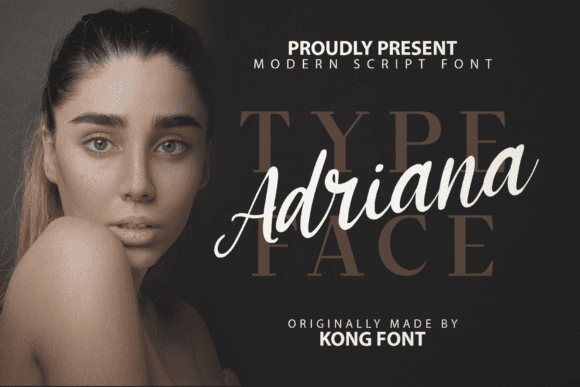
Fonte Adriana para títulos, pôsteres e projetos de identidade visual.
Esta é uma fonte de exibição moderna, criada para designers que precisam de clareza e elegância em tipografia de grande formato. Adriana apresenta traços refinados e espaçamento equilibrado, tornando-a ideal para títulos, layouts editoriais e identidade visual de marcas.
Como fonte, Adriana traz precisão e estilo a logotipos, materiais de marketing e composições de pôsteres. Seu design minimalista garante legibilidade, mantendo uma forte identidade visual em todas as mídias.
Seja para construir uma marca, criar peças gráficas promocionais ou desenvolver composições tipográficas arrojadas, Adriana oferece a flexibilidade e o requinte que seu trabalho exige.
O que você pode fazer
- Manchetes de revistas e da web
- Títulos de pôsteres e folhetos
- Logotipos e marcas denominativas
- Embalagem e sinalização do produto
- Banners ousados e campanhas visuais
Por que você vai adorar
- Design moderno, limpo e profissional.
- Excelente legibilidade em tamanhos grandes e pequenos.
- Ideal para branding e textos de alto impacto.
P: Que tipo de fonte é Adriana?
A: Adriana é uma fonte de exibição elegante, projetada para títulos impactantes, identidade visual moderna e pôsteres estilosos.
P: A impressão ficará nítida em cartazes e placas?
A: Sim, a fonte Adriana foi otimizada para oferecer nitidez em grandes formatos, sendo ideal para pôsteres, banners e sinalização.
P: É adequado para uma identidade visual minimalista?
A: Sem dúvida. As linhas simples e o estilo moderno de Adriana combinam perfeitamente com uma estética minimalista e luxuosa.
| Recurso | Fonte Adriana | Fonte de exibição genérica A | Genérico Moderno Serifado B |
| Estilo da fonte | Exibição limpa e moderna | Fonte de pôster em negrito | Serifa de bordas afiadas |
| Melhor uso | Identidade visual, títulos, embalagens | Panfletos e cartazes informais | Identidade editorial e de marca sofisticada |